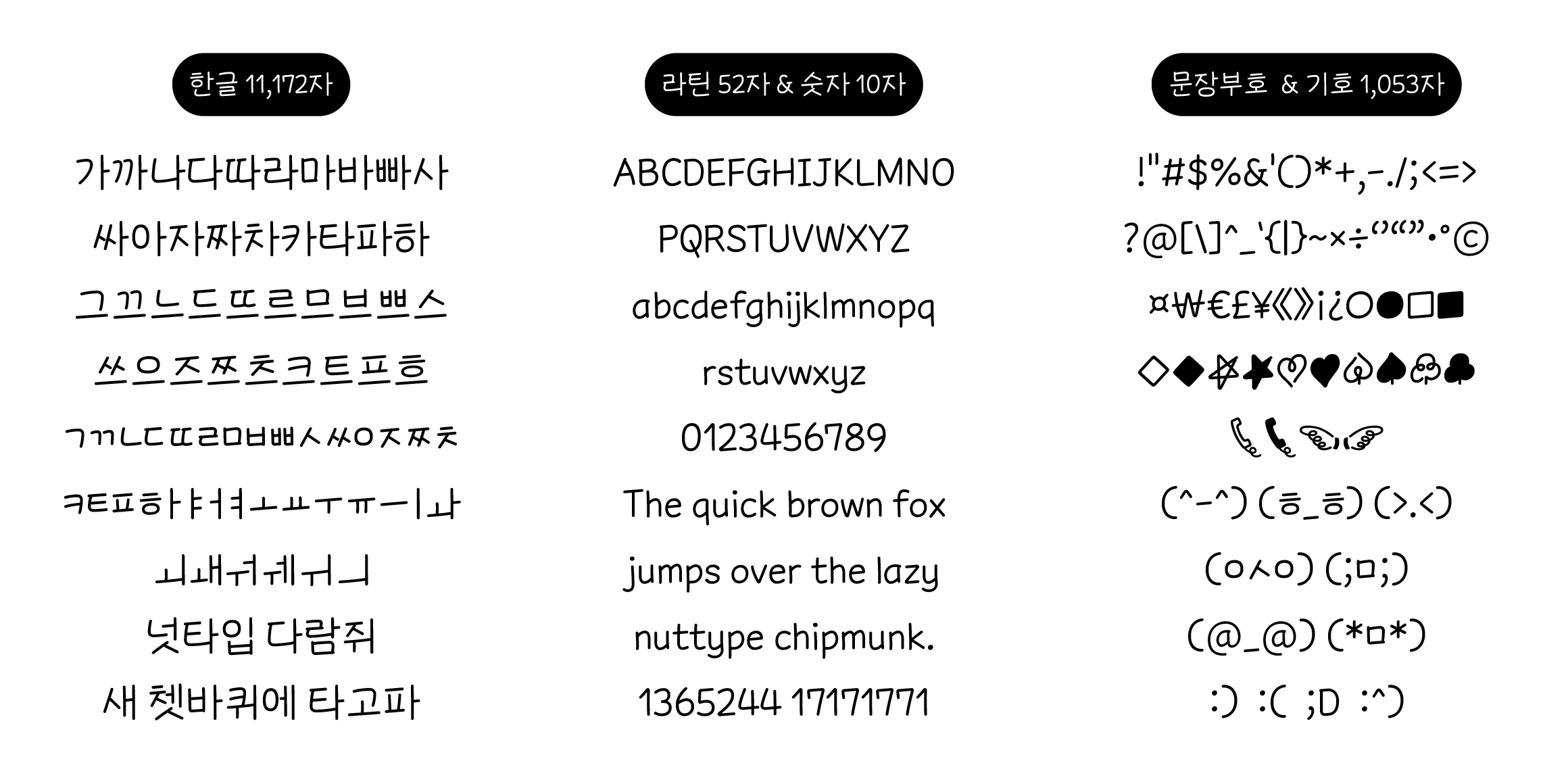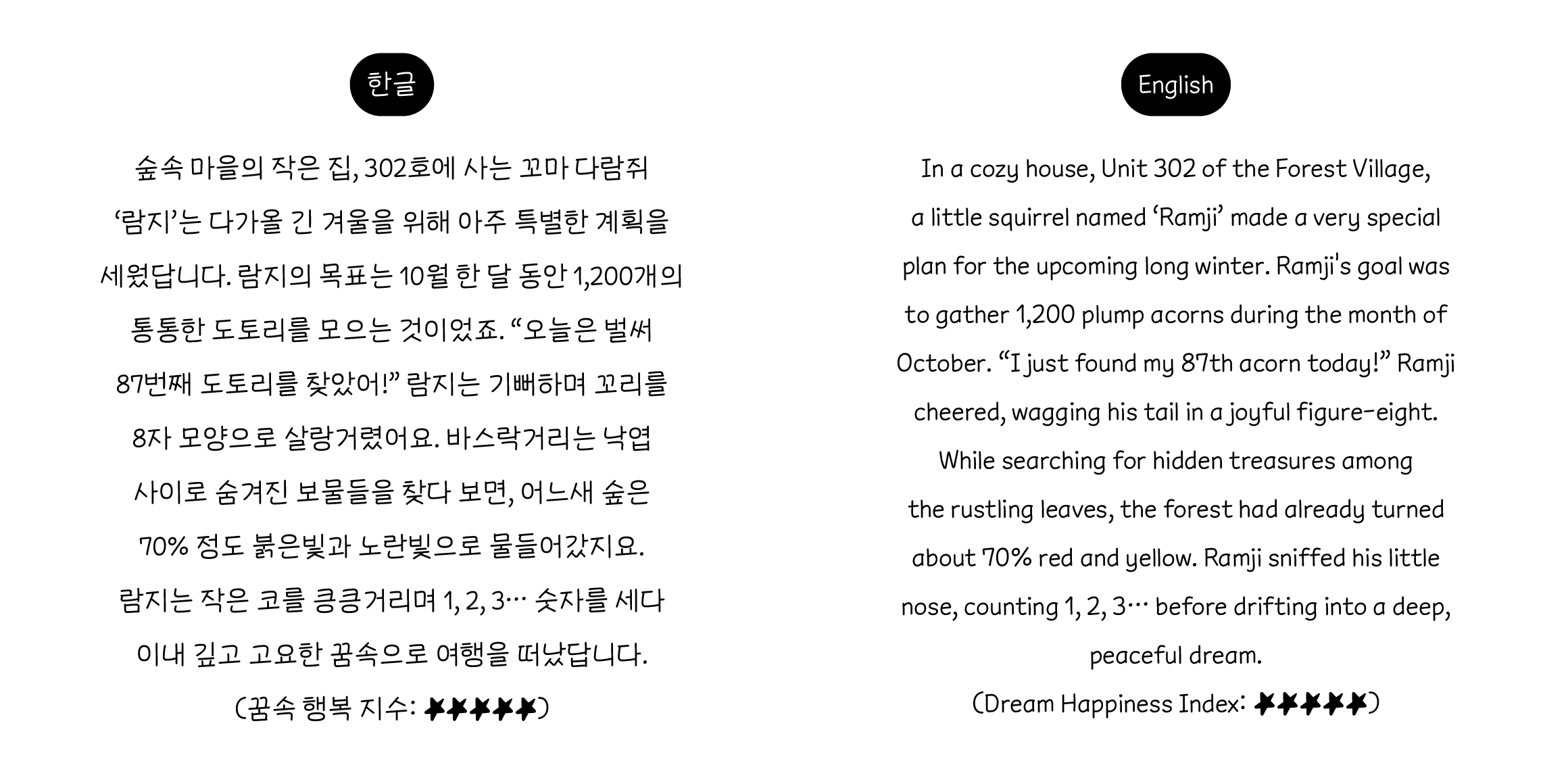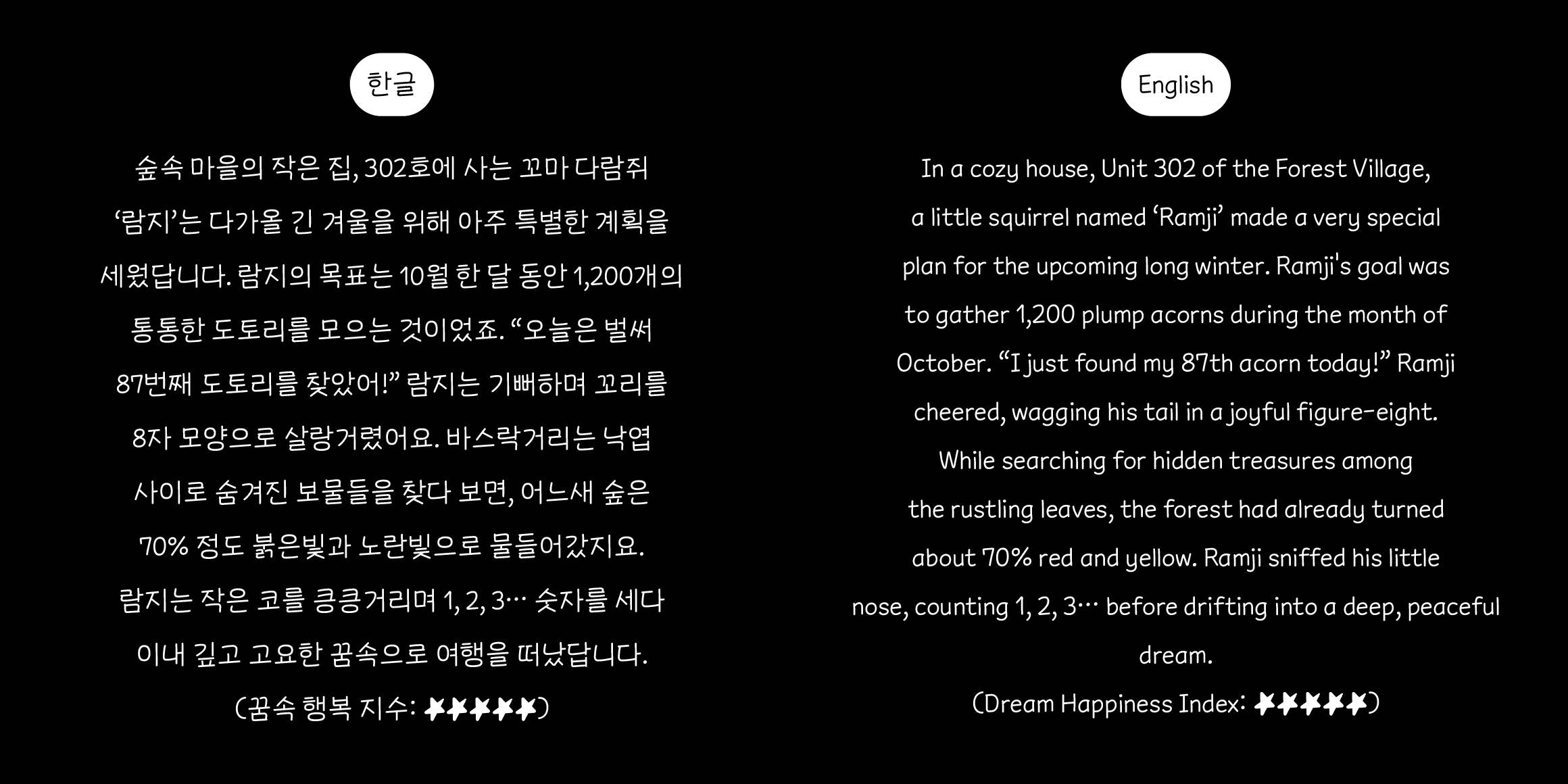
nut 빨간안경람지
Nuttype
분류 Script,디스플레이,손글씨
nut 빨간안경람지 font in use
왜인지 빨간 안경을 쓰면 평범했던 나도 시네필?!
오늘도 영화 관람 후 한 줄 평을 남기기 위해 고심하는 빨간안경람지. 간결한 문장 속 허를 찌르는 핵심 한 방이 부족한데… 한 문장 쓰는 데 드는 시간이 영화 상영 시간보다 길어진다.
• nut 빨간안경람지 / nut Red Glasses Ramji